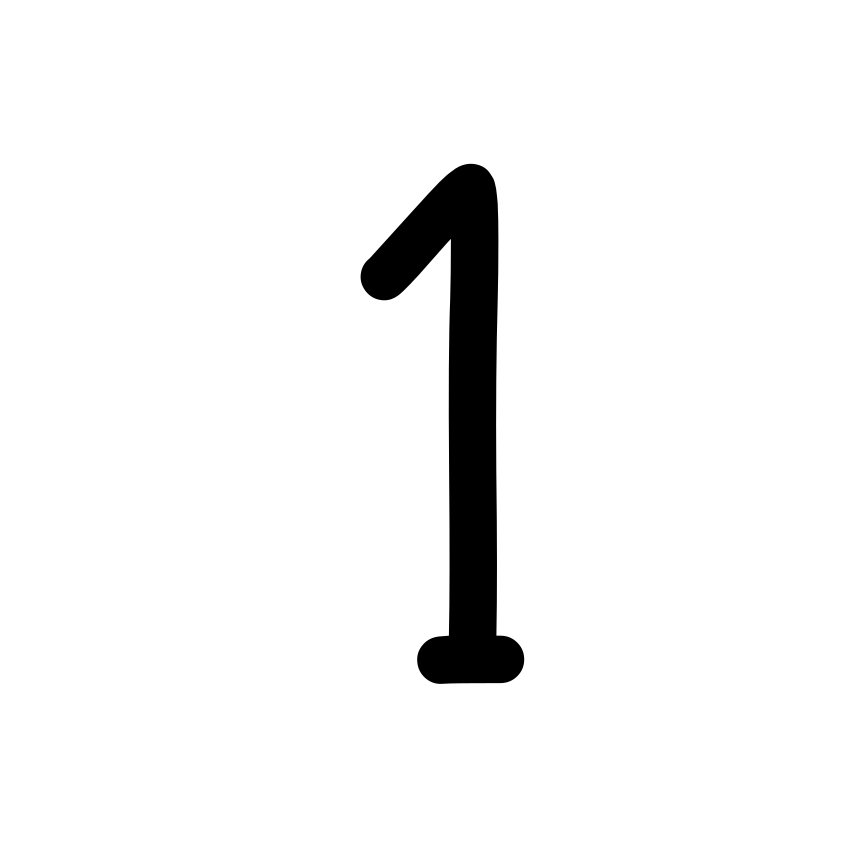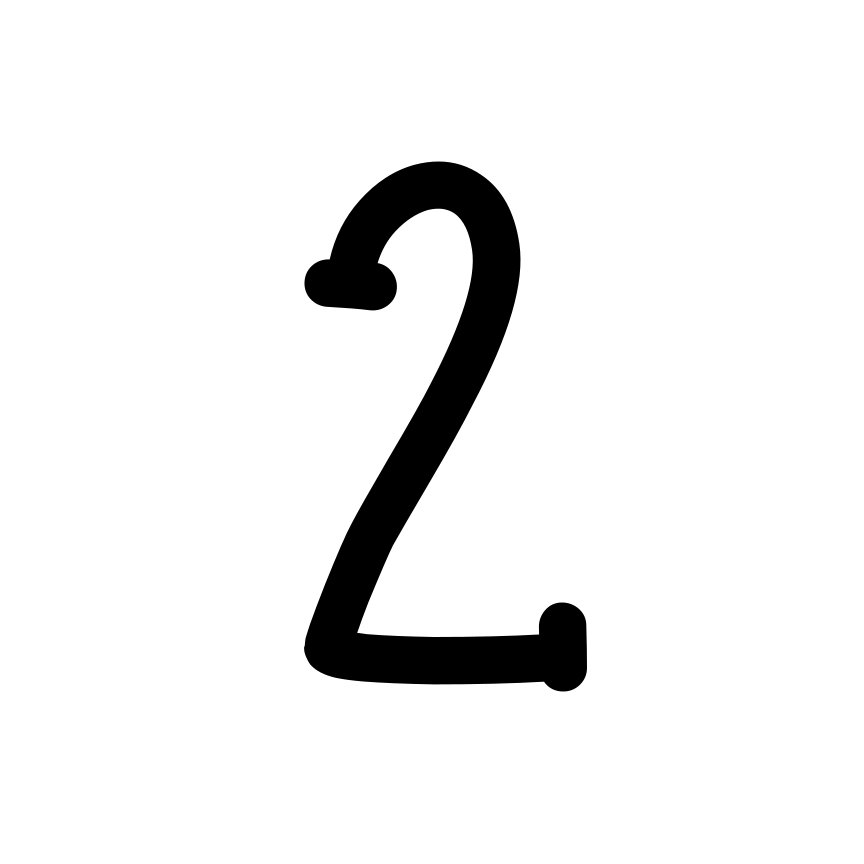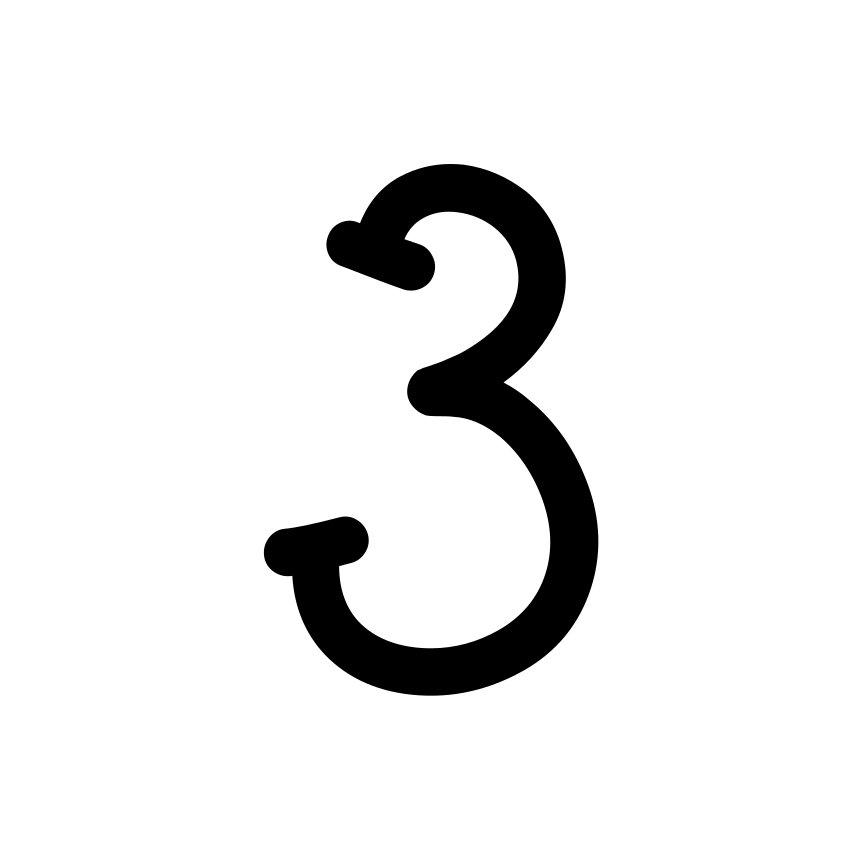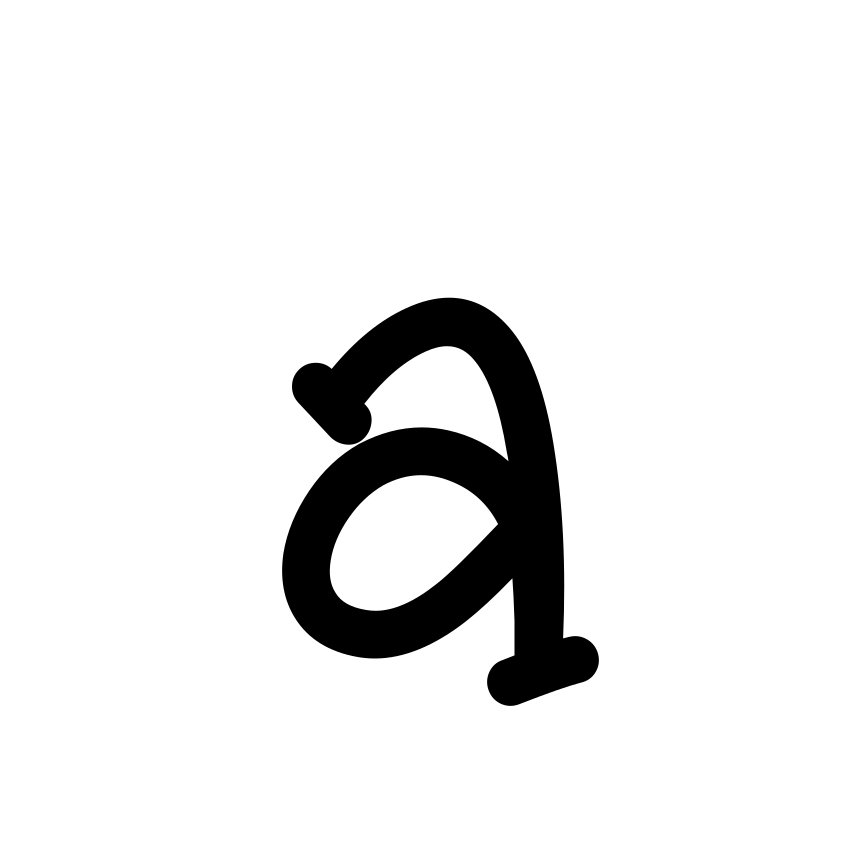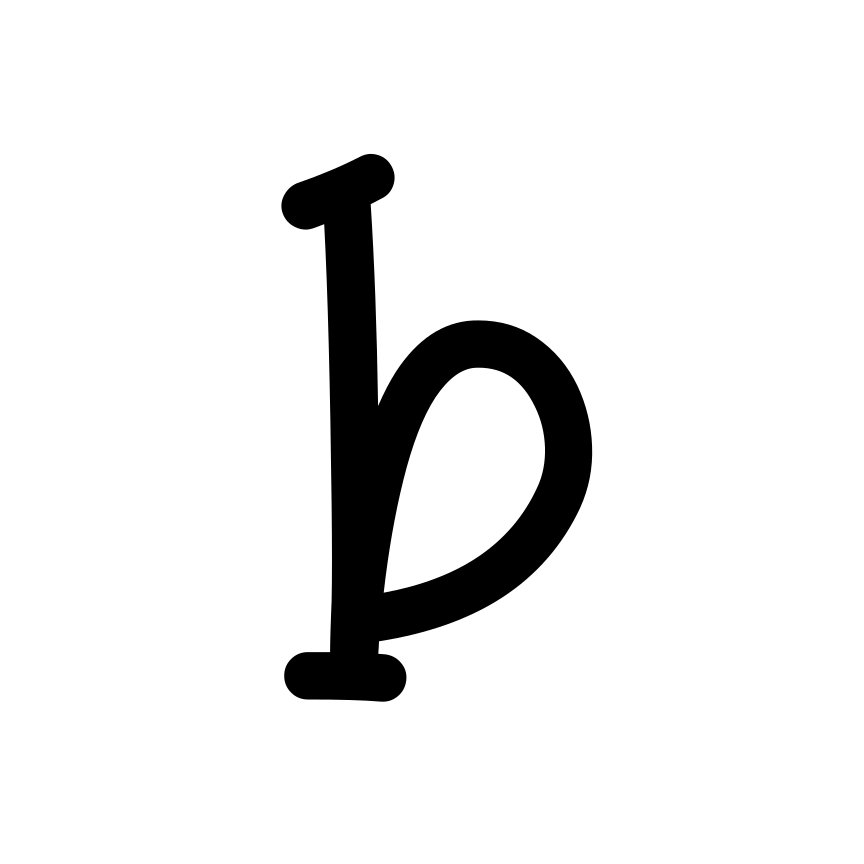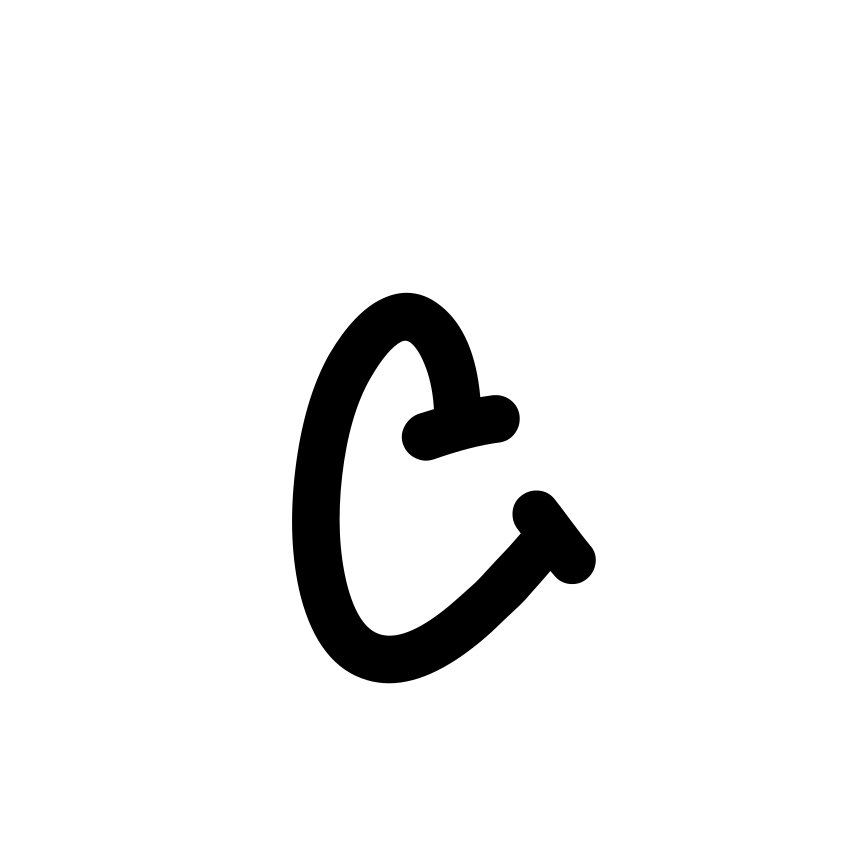
Nursery Playtime Monogramm Schriftart – Niedliches handgeschriebenes Alphabet mit Grossbuchstaben, Kleinbuchstaben, Zahlen und Satzzeichen | Cricut-kompatibel
• Die Nursery Playtime Monogramm Schriftart ist ein fröhliches handgeschriebenes Alphabet, inspiriert von verspielten Schriftstilen aus der frühen Kinderwelt. Die Buchstaben besitzen eine weiche, handgezeichnete Optik mit leicht unregelmässigen Linien und runden Formen, die der Schrift eine freundliche und lebendige Ausstrahlung verleihen.
• Die Schrift enthält Grossbuchstaben, Kleinbuchstaben, Zahlen von 0–9 sowie eine praktische Auswahl an Satzzeichen. Durch ihren verspielten Stil eignet sie sich besonders gut für Monogramm-Designs, bei denen Namen und Initialen klar hervorgehoben werden sollen.
• Mit ihrem einfachen handschriftlichen Erscheinungsbild passt die Schrift ideal zu kreativen Bastelprojekten, bleibt dabei jedoch gut lesbar und optisch ausgewogen. Sie verleiht Designs eine warme, jugendliche Atmosphäre und sorgt für einen entspannten, freundlichen Charakter in vielen kreativen Anwendungen.